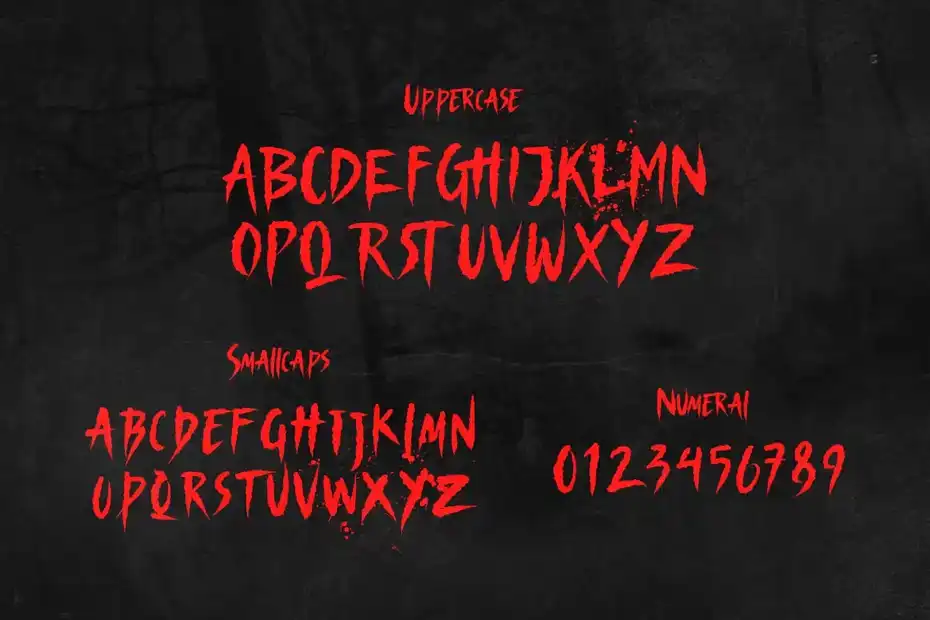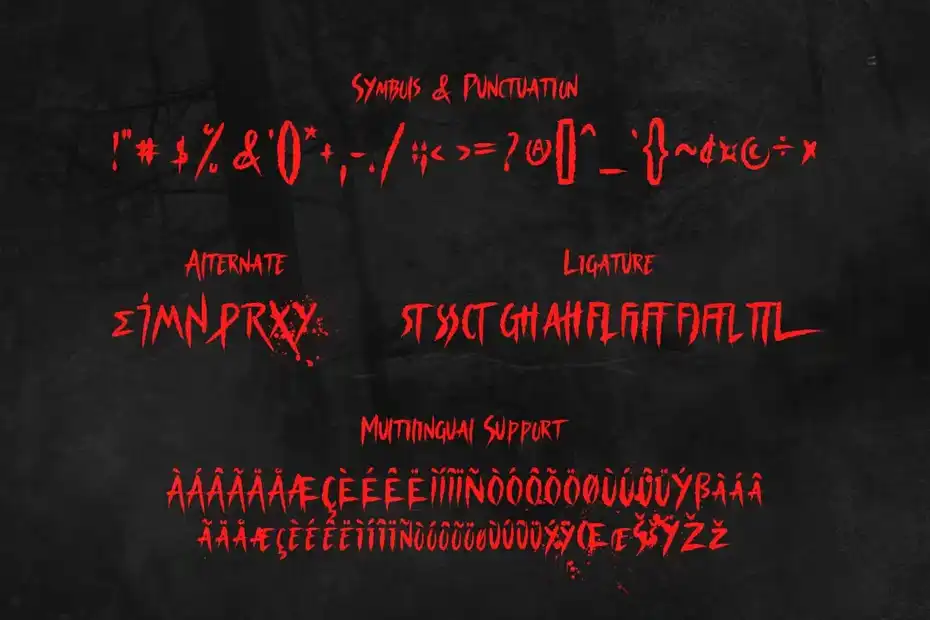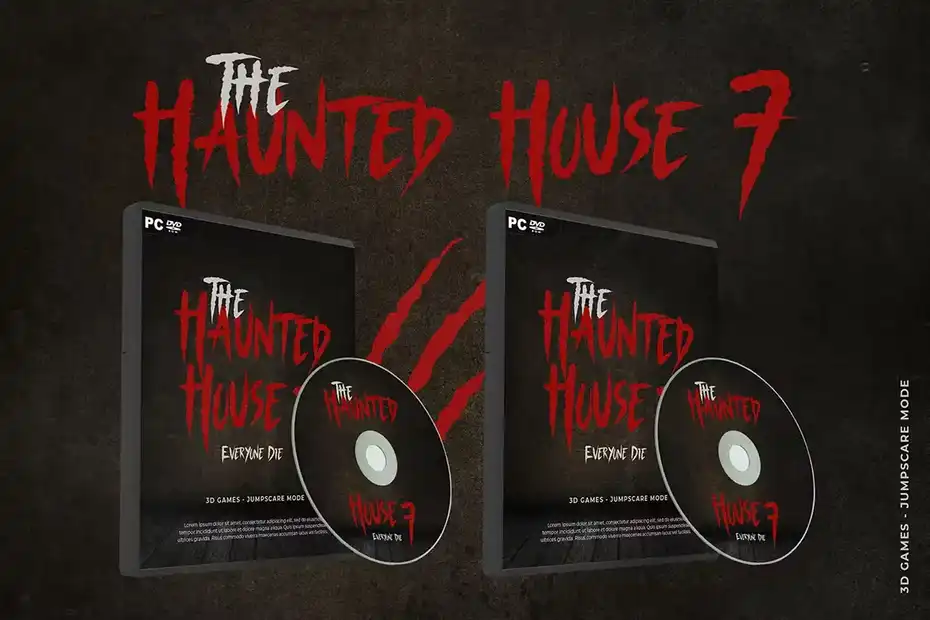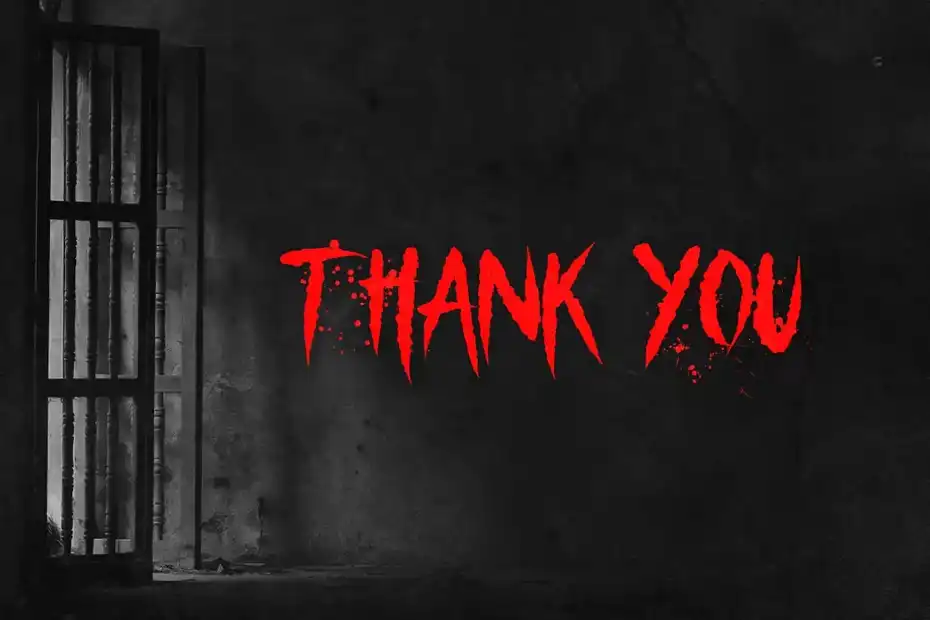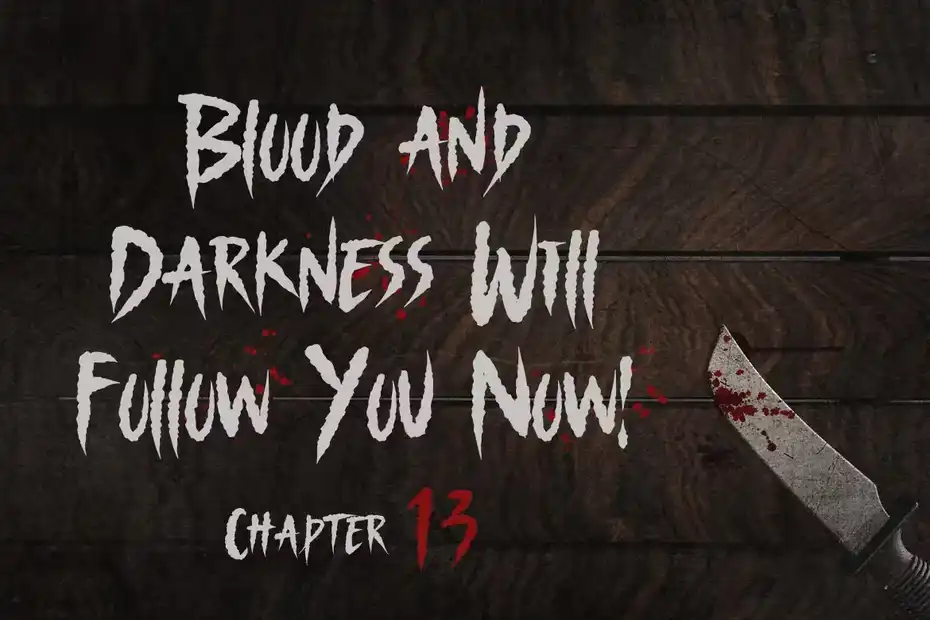
دانلود فونت انگلیسی ترسناک Nightscary – Horror and Scary Font
فونت انگلیسی ترسناک Nightscary – Horror and Scary Font : این مجموعه شامل یک فونت انگلیسی دست نویس است که برای فیلم های ترسناک و هالووین مناسب میباشد.
• عنوان مجموعه: Nightscary – Horror and Scary Font